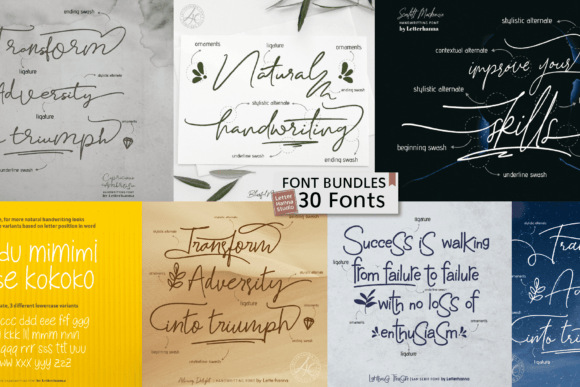
Handwritten Bundle
Handwritten Bundle : L’ultime collection de polices manuscrites
Vous cherchez une façon unique d’apporter une touche personnelle à vos projets de design ? Le Handwritten Bundle est votre réponse. Cette pack de polices manuscrites, riche en styles variés, offre une palette créative sans limite pour logos, invitations, affiches, web‑design ou même typographie de livres.
Fonctionnalités clés qui font la différence
- Polices PUA encodées : accédez à tous les glyphes, swashes, ligatures et caractères spéciaux sans effort.
- Swashes d’ultra‑début et de fin : ajoutez une touche dramatique aux premières et dernières lettres.
- Ornements et décorations : enrichissez vos titres et vos sous‑titres de motifs sophistiqués.
- Support multilingue : travaillez en anglais, espagnol, français, allemand, italien… sans limites.
La collection complète – 30 polices exclusives
- Abellaice
- Versatile Azalea
- Blooming Valerian
- Majestic Wisteria
- Groovy Soumaya
- Brave Youthquakes
- Ravishing Solidago
- Lovely Hydrillas
- Amiable Forsythia
- Jettiares
- Hasibuan
- Bingkisan
- William Jameson
- Scarlet Mackenzie
- Bohemian Cassidy
- Zara Amorett
- Angelina Malika
- Hosperity
- Sparkling Horizon
- Magical Journey
- Thoughtful Pathways
- Blossoming Constellation
- Capricious Ambrosia
- Lighthouse Treasure
- Stardelle
- Alluring Delight
- Banana Moonpie
- Timeless Wonderland
- Seashell Paradise
- Blissful Mountain